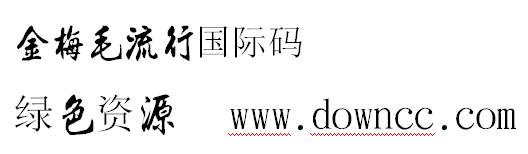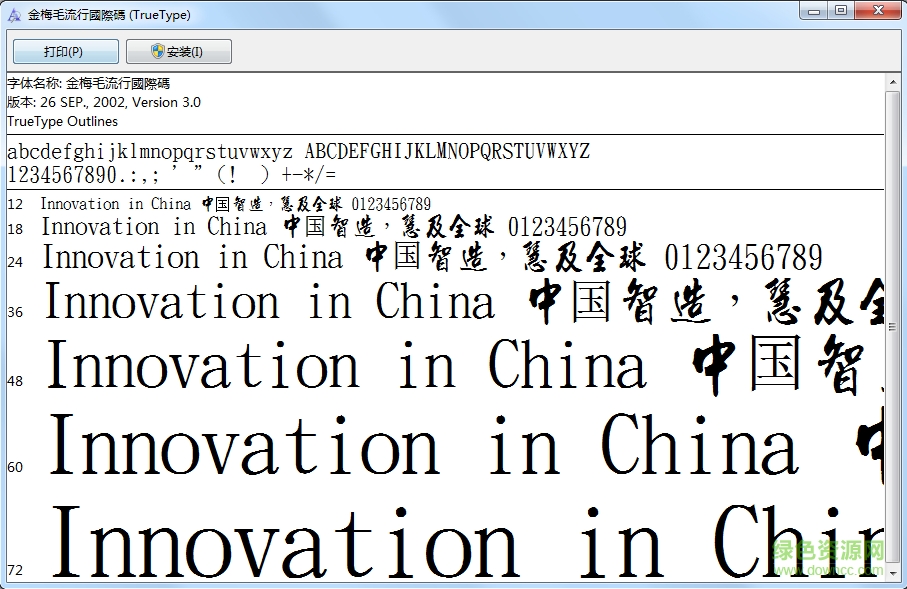
金梅毛流行國(guó)際碼是一款繁體輸入的書法字體,簡(jiǎn)約大方的造型很能贏得觀賞人士們的喜愛,綠色資源網(wǎng)獨(dú)家提供這款字體,歡迎大家下載使用!
金梅毛流行國(guó)際碼字體是一款毛筆書法繁體字體,本作品可用于廣告設(shè)計(jì)字體、網(wǎng)頁(yè)設(shè)計(jì)字體、包裝設(shè)計(jì)字體、 屏幕顯示字體等。